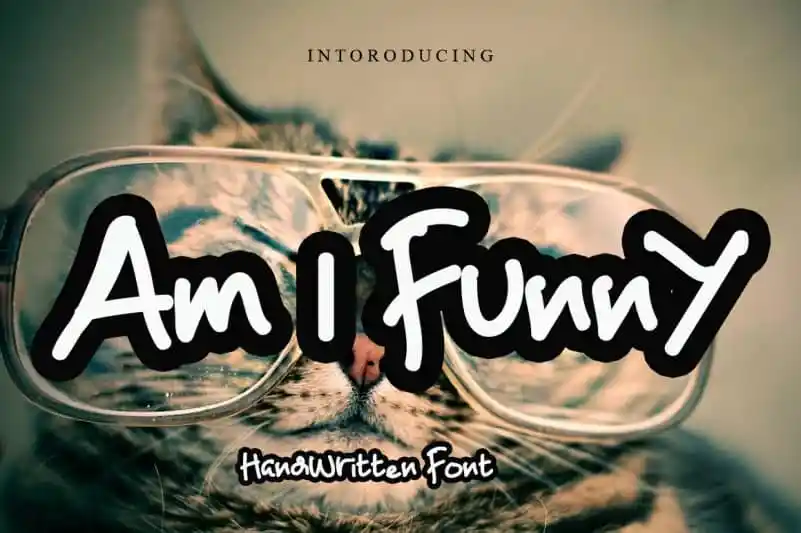
Am I Funny Display Font – Fonte Grátis
Am I Funny Display Font
A Am I Funny Display Font é uma fonte relaxada e fresca, inspirada na escrita a mão. Suas características naturais e únicas a tornam perfeita para um grande número de projetos gráficos. Esta fonte oferece uma experiência única que irá cativar e divertir o seu público, seja em letras grandes ou pequenas. Experimente com essa bela fonte e descubra as inúmeras possibilidades criativas que ela tem a oferecer. Com Am I Funny Display Font, você pode explorar seu lado mais descontraído e irônico. Seja você um designer de logotipo, um blogueiro ou até mesmo um produtor de conteúdo online, essa fonte vai te ajudar a destacar-se no mundo do design gráfico. Experimente hoje e comece a brincar com suas criações!